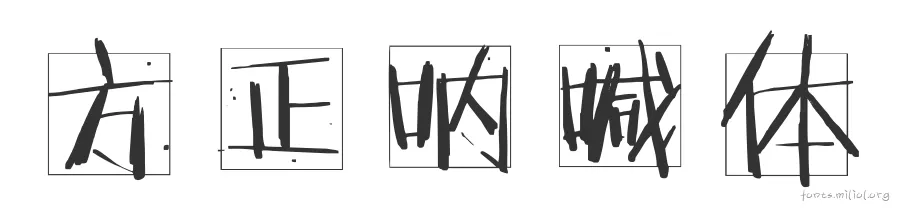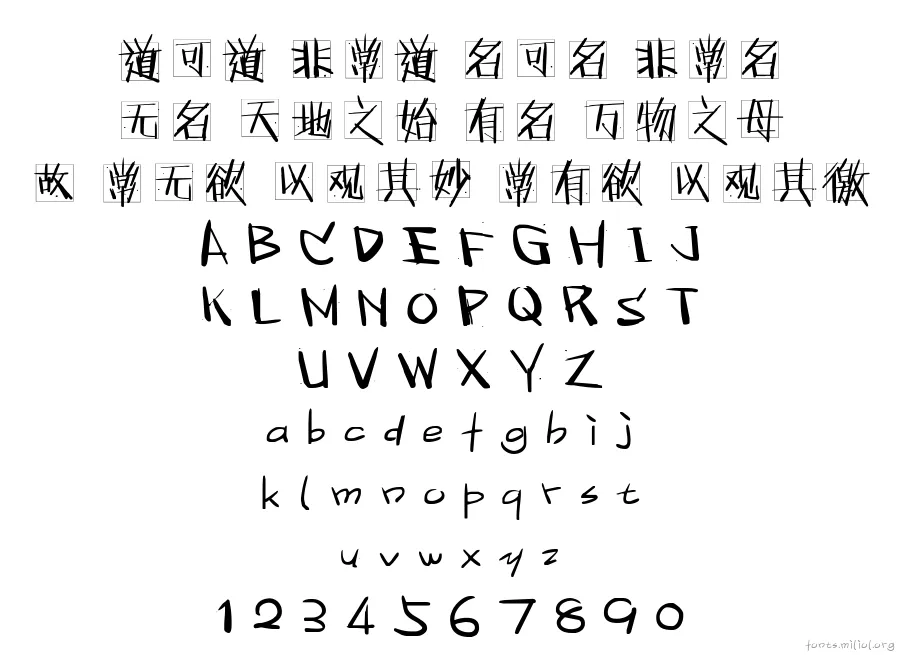
方正呐喊体 (FZNHT) 字体下载
**方正呐喊体 (FZNHT) 字体简介**
方正呐喊体(FZNHT)是一款极具视觉冲击力的中文字体,由方正字库设计并发布。其笔画粗犷有力,结构张扬奔放,整体风格充满力量感和情绪张力,适合用于海报、标题、广告等需要突出表现力的设计场景。
这款字体的设计灵感来源于“呐喊”这一动作所传递的强烈情感,字形在传统黑体的基础上融入了更多动态元素,笔画末端略带尖锐感,增强了视觉上的冲击性。方正呐喊体适用于艺术创作、品牌宣传、社交媒体等多种领域,尤其适合需要表达激情、叛逆或前卫风格的设计项目。
方正呐喊体 字体映射图